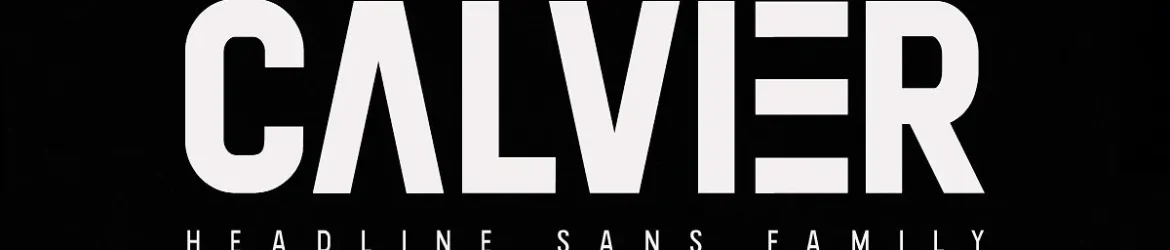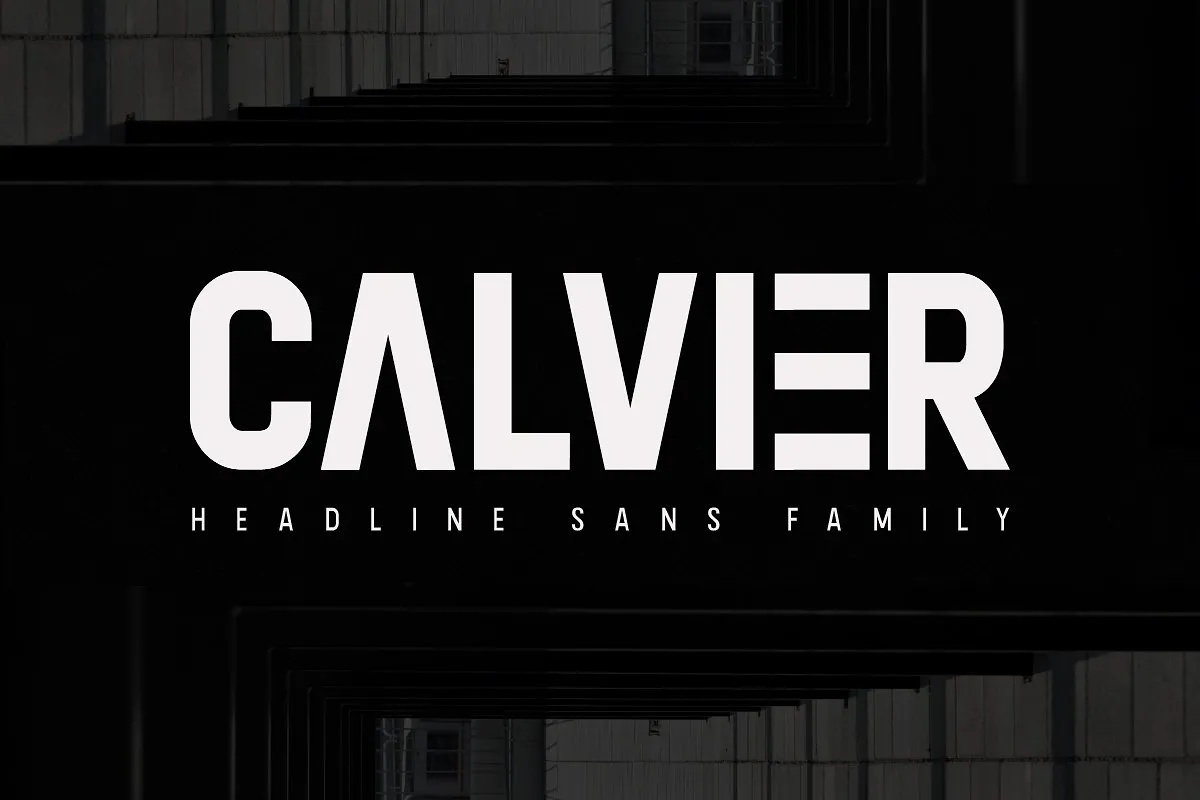
Calvier Sans Font Family – Fonte Grátis
Calvier Sans Font Family
A Calvier Sans é uma família de fontes serifadas modernas e versáteis que oferece um visual moderno e claro. Inspirada nos encantadores desenhos de fontes antigas e clássicas, ela foi projetada para criar uma impressão impactante e elegante tanto para cabeçalhos, logomarcas quanto para posters. Além disso, a Calvier possui detalhes semi-humanistas e semi-geometrizados, o que adiciona um tom de personalidade ao seu design. Suas linhas finas proporcionam uma leitura confortável e clara em qualquer situação. A família tem quatro pesos: Regular, Italic e estilo de hélice, além do Hollow Style. A Calvier Sans Family é uma escolha inteligente para quem deseja destacar seus projetos na impressão, vídeos, cabeçalhos e redes sociais sem perder a facilidade de leitura. Suas linhas fortes e modernas garantem que seu design sempre seja notável e confortável para os olhos do usuário. Independentemente de ser usada isoladamente ou em conjunto com outros elementos gráficos, ela se torna o centro dos olhos e um recurso indispensável na criação de qualquer projeto visual.